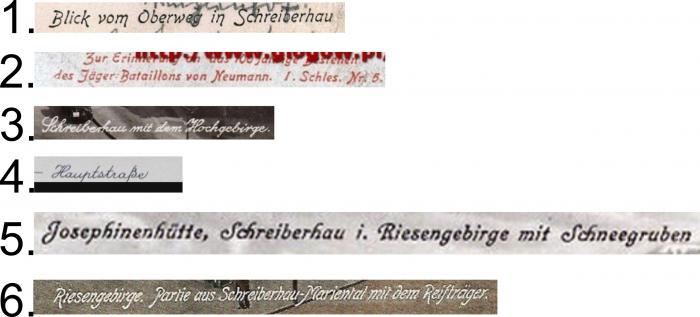
Suche dringend Namen und Bezugsquelle folgender Schriften
Ich sammele ohne kommerzielle Interessen digitale Ansichtskarten (Zeitraum ca. 1890 - 1940) und möchte diese ggf. nachbessern.
Dazu brauche ich dringend die Namen und Bezugsquellen nachstehender Schriften.
… digitale Ansichtskarten (Zeitraum ca. 1890 - 1940)
Was die Schriften angeht: Da wirst Du, wenn überhaupt, nur Annäherungen finden. Damalige Farbpostkarten wurden häufig lithographiert, die Schrift mitunter handgemacht. Da kommt man nicht einmal mit den gängigen Bleisatzschriften weiter (und selbst die sind ja heute nicht alle für Rechner verfügbar).
DEm kann ich nur beipflichten. Mein Onkel, Gustav Peyk hat noch bis in die 1980er Jahre für einen Postkartenverlag handgeschriebene Schriften erstellt.